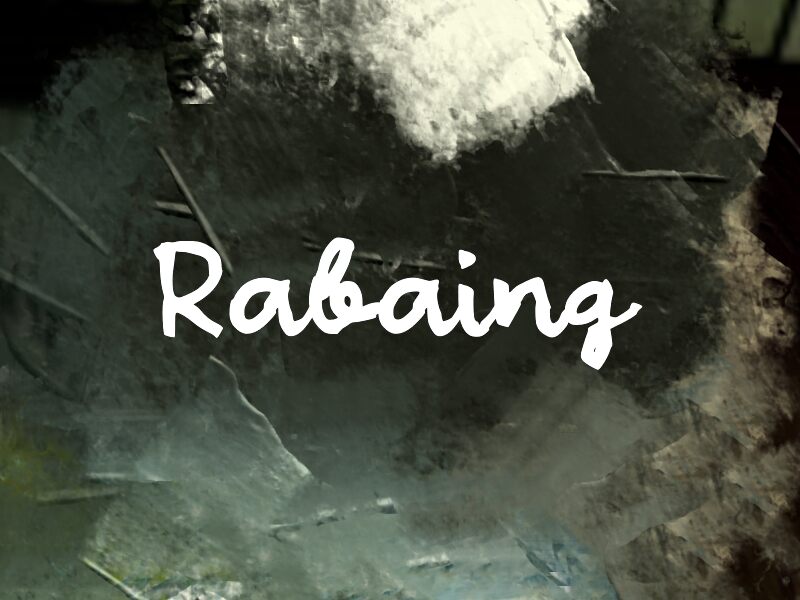
Rabaing от Wep — это бесплатный кистевой шрифт с легким рукописным настроением и темной, насыщенной чернильной текстурой. Буквы выглядят так, будто их нарисовали одним уверенным движением: широкие округлые формы здесь сочетаются с резкими узкими соединениями и острыми штрихами, которые придают ритму живость, избегая излишней отполированности.
Он органично смотрится в заголовках плакатов, брендинге кофеен, на обложках альбомов, упаковке и в социальных сетях — везде, где требуется бесплатный шрифт, который выглядит непосредственно, по-человечески и с легкой небрежностью. Благодаря тому, что штрихи то сгущаются, то расходятся неровными волнами, Rabaing также отлично подходит для коротких цитат, набросков логотипов и выразительных надписей.
Презентация и наглядный образец шрифта Rabaing